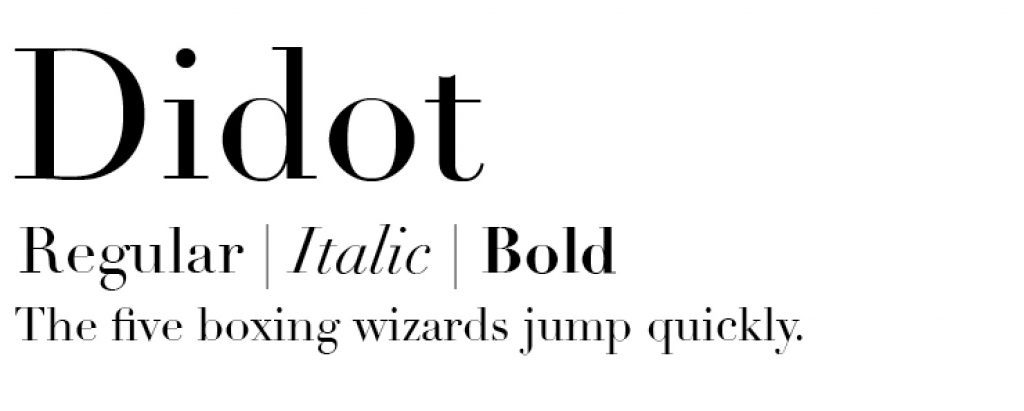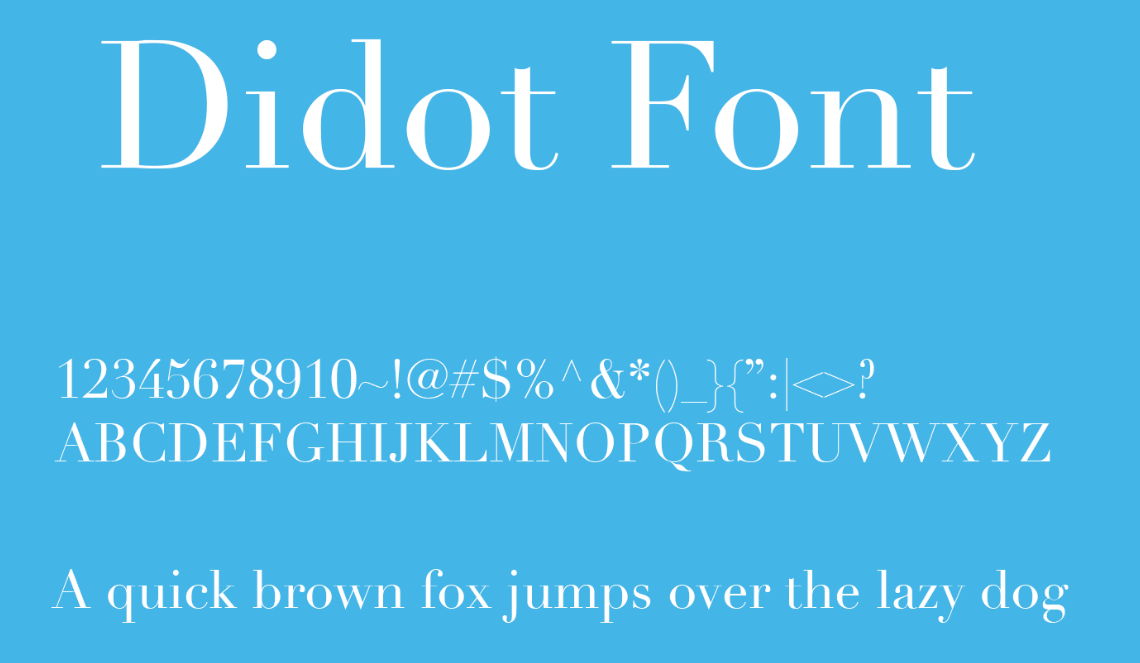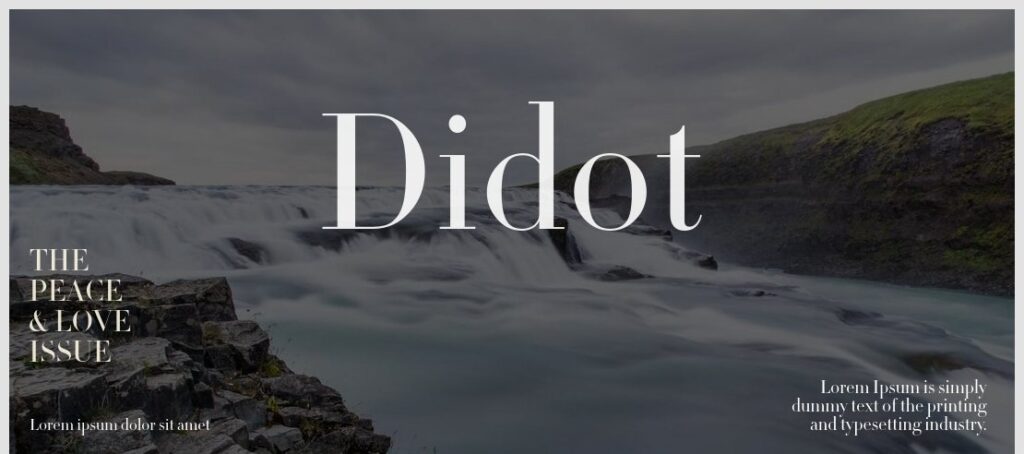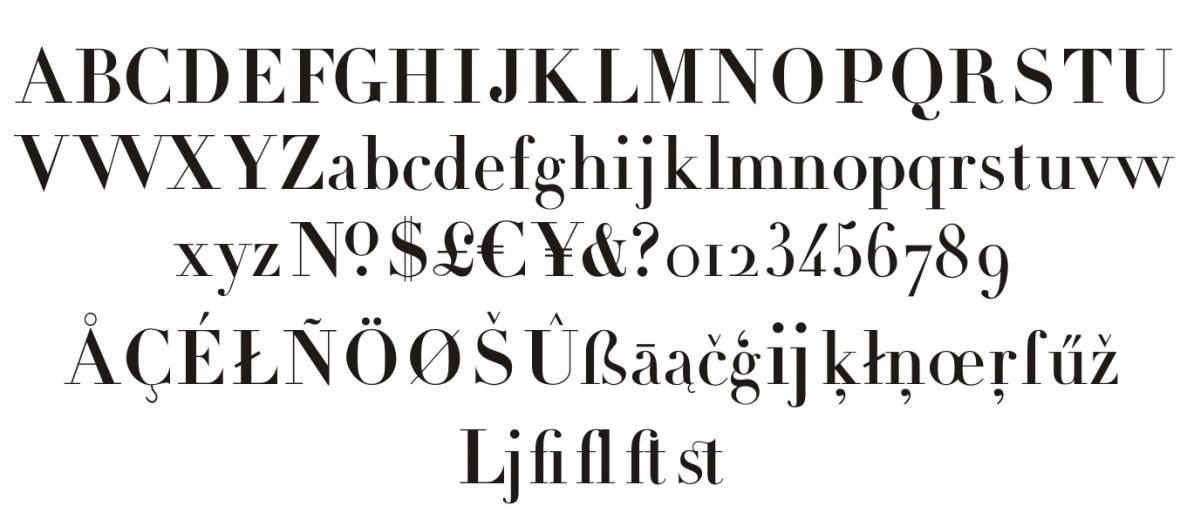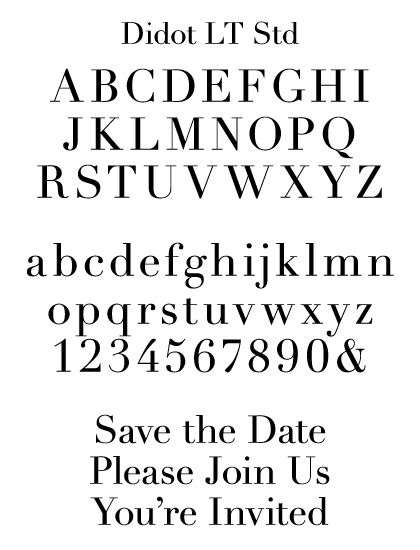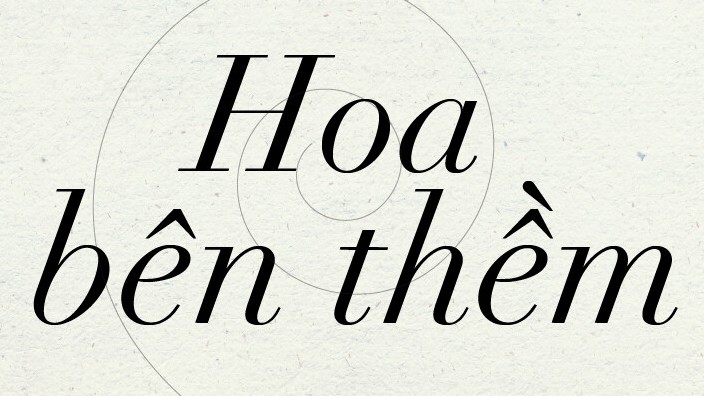
Font UVF Didot là một trong những biểu tượng kinh điển của dòng Modern Serif, gắn liền với các ấn phẩm thời trang xa xỉ và những công trình kiến trúc mang hơi thở quý tộc châu Âu. Với đặc trưng là độ tương phản gắt gao giữa nét đứng dày dặn và nét ngang thanh mảnh như sợi chỉ, kiểu chữ này mang lại vẻ ngoài lịch lãm, tinh tế cho các bản vẽ phối cảnh biệt thự, hồ sơ năng lực hay bảng hiệu homestay cao cấp.
Tinh thần quý phái của bộ phông chữ font UVF Didot trong thiết kế
Cấu trúc chữ đứng thẳng với góc chân vuông vức không có đường cong chuyển tiếp, tạo nên hiệu ứng thị giác dứt khoát và thời thượng. Phiên bản font Didot Việt hóa do UVF xử lý đã chuẩn hóa hệ thống dấu thanh tiếng Việt một cách khéo léo, giúp các dấu sắc, huyền, hỏi, ngã hòa nhập tự nhiên vào bố cục chữ mà không làm phân tán sự chú ý khỏi nét thanh mảnh đặc trưng của bộ gốc.
Khả năng truyền tải thông điệp của kiểu chữ này gắn liền với các giá trị về sự xa hoa, đẳng cấp và tính riêng biệt. Khi xuất hiện trên các bề mặt vật liệu kiến trúc hiện đại như kính cường lực, inox gương mạ vàng hay đá cẩm thạch, Didot ngay lập tức thiết lập một chuẩn mực thẩm mỹ trang nhã. Đây là giải pháp phù hợp để định hình ngôn ngữ thị giác cho các dự án nghỉ dưỡng hạng sang, văn phòng cao cấp trong nhà container hoặc các thương hiệu kiến trúc muốn khẳng định phong cách chuyên nghiệp, khác biệt.
Tư vấn từ chuyên viên: UVF Didot sở hữu nét thanh rất mỏng và độ tương phản cực kỳ cao. Để bản thiết kế đạt hiệu quả thị giác tốt, bạn chỉ nên sử dụng phông chữ này cho các tiêu đề chính hoặc cụm từ ngắn ở kích thước lớn. Đối với các đoạn văn bản mô tả kỹ thuật chi tiết, hãy phối hợp cùng một phông chữ không chân (Sans-serif) trung tính để người xem đọc thông tin thuận tiện.
03 Ứng dụng phông chữ Didot vào không gian công trình thực tế
Nhờ diện mạo sang trọng và tính thẩm mỹ cao cấp, bộ phông chữ này mang lại giá trị thực tế lớn trong khâu trang trí và quảng bá các dự án kiến trúc hiện đại:
- Bảng hiệu cho Villa và Boutique Homestay: Những nét chữ thanh lịch của Didot rất ăn ý khi gia công cắt laser chữ nổi inox mạ vàng gương hoặc đồng xước. Phông chữ này giúp mặt tiền của các căn homestay lắp ghép toát lên vẻ quý phái, tạo dấu ấn thị giác khó quên cho du khách.
- Bìa hồ sơ năng lực kiến trúc: Sử dụng font Didot Việt hóa cho tên dự án và tiêu đề các chương mục giúp hồ sơ trông như một tạp chí kiến trúc danh giá, nâng cao vị thế và sự tin cậy của đơn vị thiết kế đối với chủ đầu tư.
- Hệ thống biển số phòng và chỉ dẫn nội khu: Bạn có thể dùng phông chữ này để in trên kính hoặc khắc chìm trên vật liệu gỗ tự nhiên, tạo điểm nhấn nhẹ nhàng nhưng sắc nét cho không gian hành lang và sảnh đón tiếp.
03 Lưu ý về bố cục font Didot Việt hóa giữ trọn nét sắc sảo
Để khai thác hiệu quả vẻ đẹp của dòng font thời trang quý tộc này mà không làm ảnh hưởng đến khả năng đọc của bản vẽ, người thiết kế nên lưu tâm một số kinh nghiệm sau:
- Kiểm soát kích thước hiển thị: Tránh sử dụng Didot ở kích thước quá nhỏ (dưới 14pt trong in ấn), vì nét thanh mỏng như sợi tơ có thể bị biến mất do độ phân giải máy in hoặc hiện tượng nhòe mực trên các chất liệu giấy nhám.
- Nới rộng khoảng cách ký tự: Đối với các tiêu đề viết hoa toàn bộ, việc kéo giãn nhẹ khoảng cách giữa các chữ cái sẽ làm tăng tính trang trọng, giúp bố cục thông thoáng và mang đậm phong cách tạp chí cao cấp.
- Lựa chọn nền màu tương phản mạnh: Didot phát huy hiệu quả thị giác cao khi đặt trên các gam màu đơn sắc có chiều sâu như đen tuyền, trắng ngọc trai, xanh navy đậm hoặc xám than chì để tôn vinh sự tinh xảo của từng chân chữ.